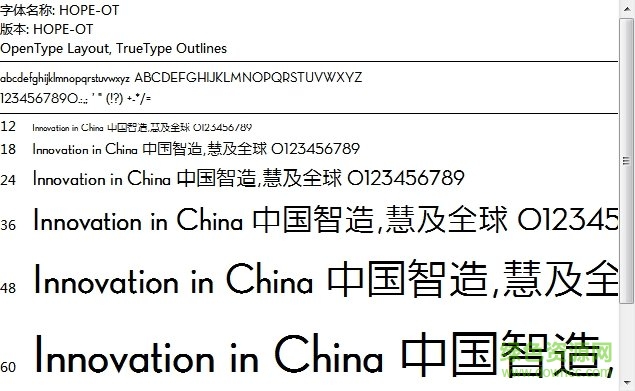
努比亞櫻木體
櫻木體是一款來(lái)源于努比亞社區(qū)分享的藝術(shù)字體,字庫(kù)全支持商標(biāo)符號(hào)、淘寶亂碼,讓你的文字更加端正好認(rèn),無(wú)過(guò)多的修飾,還原文字本身的質(zhì)樸之感,來(lái)綠色資源網(wǎng)下載試試吧!
櫻木體預(yù)覽
櫻木體+二次元
櫻木體字體包含兩款字體,一款是原生態(tài)的簡(jiǎn)潔版,一款是二次元美化后的海上自用版,但字體本身模板不變,線條清晰正直,讓文字也變得更加易于辨認(rèn),可以使用在多種領(lǐng)取,也可以作為你的手機(jī)字體